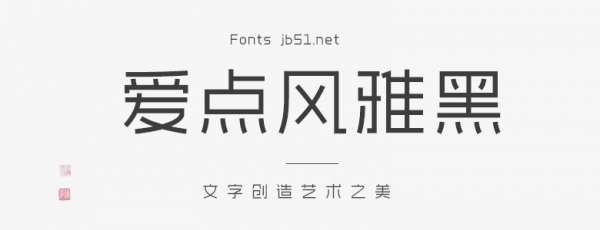
愛點(diǎn)風(fēng)雅黑是廣州愛點(diǎn)視覺文化有限公司(愛點(diǎn)字庫(kù))研發(fā)的商用免費(fèi)字體,個(gè)人及企業(yè)可永久免費(fèi)使用。該字體設(shè)計(jì)端正如砥、筆直如松,秀雅時(shí)尚,可免費(fèi)用于各類廣告、UI設(shè)計(jì)用途。